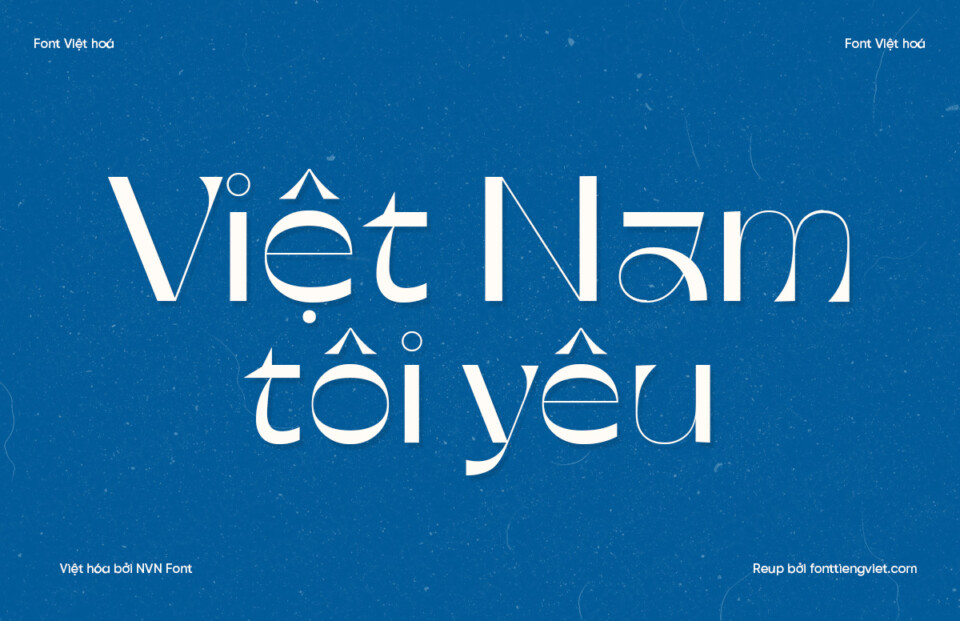
Font Việt hóa NVN Harpagan
Font Việt hóa NVN Harpagan – Bộ Font Chữ Nghệ Thuật Độc Đáo Cho Thiết Kế
Trong thế giới đồ họa hiện đại, việc lựa chọn một bộ Font Việt hóa NVN Harpagan phù hợp đóng vai trò then chốt trong việc tạo nên linh hồn cho sản phẩm sáng tạo. Font Miễn Phí luôn là ưu tiên hàng đầu của cộng đồng thiết kế Việt Nam khi tìm kiếm sự độc đáo và tính ứng dụng cao. NVN Harpagan không chỉ đơn thuần là các ký tự vô tri, mà là sự kết hợp hoàn hảo giữa nét cổ điển và hơi thở đương đại, giúp các nhà sáng tạo nội dung truyền tải thông điệp một cách ấn tượng nhất. Bộ font này được đội ngũ NVN chăm chút tỉ mỉ từng dấu thanh, đảm bảo không xảy ra lỗi hiển thị khi soạn thảo tiếng Việt, mang lại trải nghiệm mượt mà trên mọi nền tảng đồ họa phổ biến hiện nay.
Đặc điểm nổi bật của Font Việt hóa NVN Harpagan
Phong cách thiết kế mạnh mẽ và cá tính
Bộ Font Việt hóa NVN Harpagan sở hữu những đường nét sắc sảo, dứt khoát nhưng không kém phần uyển chuyển. Cấu trúc chữ được thiết kế với độ tương phản vừa phải, tạo cảm giác vững chãi và chuyên nghiệp. Đây là lựa chọn lý tưởng cho các dự án yêu cầu sự phá cách như thiết kế bìa sách, poster phim, hoặc bộ nhận diện thương hiệu cho các quán cà phê, cửa hàng thời trang mang phong cách retro. Sự cân bằng giữa các khoảng trắng và nét chữ giúp văn bản luôn dễ đọc ngay cả khi sử dụng ở kích thước nhỏ.
Khả năng tương thích và hỗ trợ tiếng Việt toàn diện
Một trong những điểm mạnh nhất của Font Việt hóa NVN Harpagan chính là bảng mã được tối ưu hóa hoàn toàn cho ngôn ngữ tiếng Việt. Các dấu câu như huyền, sắc, hỏi, ngã, nặng được đặt ở vị trí hợp lý, tránh tình trạng đè nét hoặc quá xa ký tự gốc. Điều này giúp các bạn học sinh, sinh viên hay giáo viên dễ dàng ứng dụng vào bài thuyết trình Powerpoint hoặc làm tài liệu giảng dạy mà không lo bị lỗi font hệ thống. Việc tích hợp đầy đủ các ký tự đặc biệt cũng giúp quá trình trình bày văn bản trở nên chuyên nghiệp và thẩm mỹ hơn rất nhiều.
Ứng dụng thực tế của Font Việt hóa NVN Harpagan trong đời sống
Thiết kế truyền thông và quảng cáo
Với vẻ ngoài lôi cuốn, Font Việt hóa NVN Harpagan thường xuyên xuất hiện trong các chiến dịch marketing mạng xã hội. Các designer thường dùng bộ font này để nhấn mạnh tiêu đề chính trên banner hoặc ảnh bìa Facebook nhằm thu hút ánh nhìn của khách hàng ngay từ giây đầu tiên. Ngoài ra, tính nghệ thuật của nó còn rất phù hợp để làm typography cho các câu trích dẫn truyền cảm hứng, tạo nên sức lan tỏa mạnh mẽ trong cộng đồng người dùng trẻ tại Việt Nam.
Sáng tạo trong học đường và dự án cá nhân
Đối với các bạn học sinh, việc sử dụng Font Việt hóa NVN Harpagan vào các báo cáo hay dự án ngoại khóa sẽ giúp sản phẩm cá nhân nổi bật hơn hẳn so với các font chữ truyền thống nhàm chán. Thầy cô giáo cũng có thể sử dụng font này để thiết kế các thiệp chúc mừng, bằng khen hay trang trí bảng tin lớp học nhằm tạo không khí học tập sinh động và sáng tạo. Tính linh hoạt của bộ font cho phép nó thích nghi tốt với cả in ấn lẫn hiển thị kỹ thuật số.
Kết luận về bộ Font Việt hóa NVN Harpagan